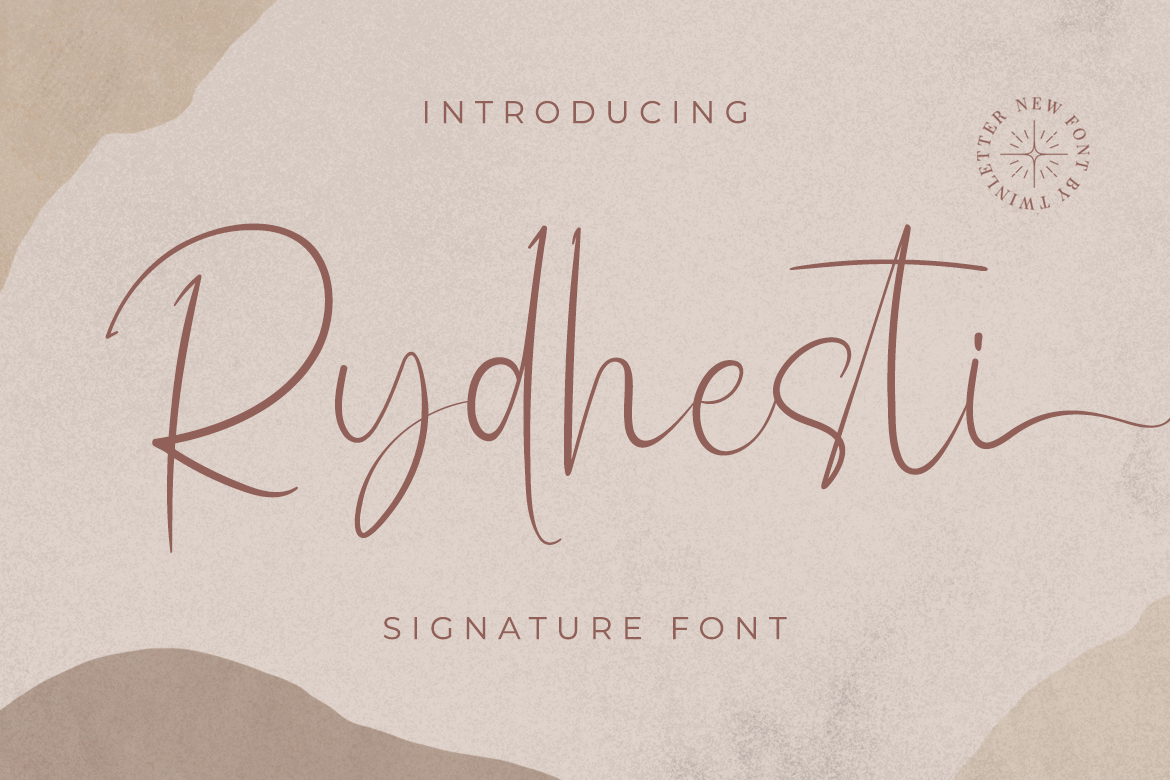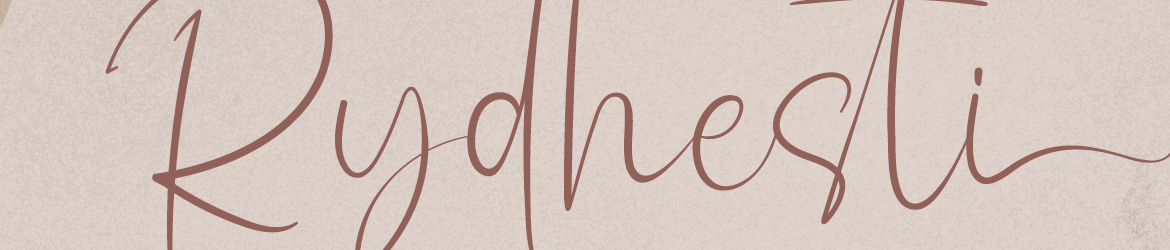
A Rydhesti Font é uma elegante tipografia script que traz sofisticação ao seu design. Seu traço fino e refinado torna-a perfeita para criar invitations de casamento memoráveis, arte impressa que destacará sua personalidade, postagens nas redes sociais impactantes e muito mais. Além disso, é uma fonte PUA (Proprietary User Area) em código, o que significa que você terá acesso fácil a todos os caracteres e as variações curvilíneas. A Rydhesti é ideal para quem procura um estilo sofisticado sem comprometer a versatilidade na criação de diferentes tipos de mídia.